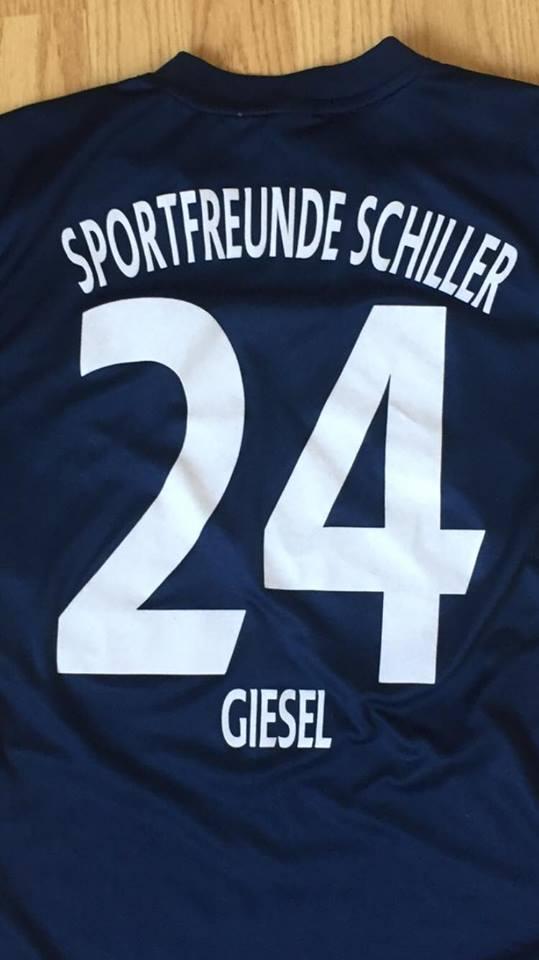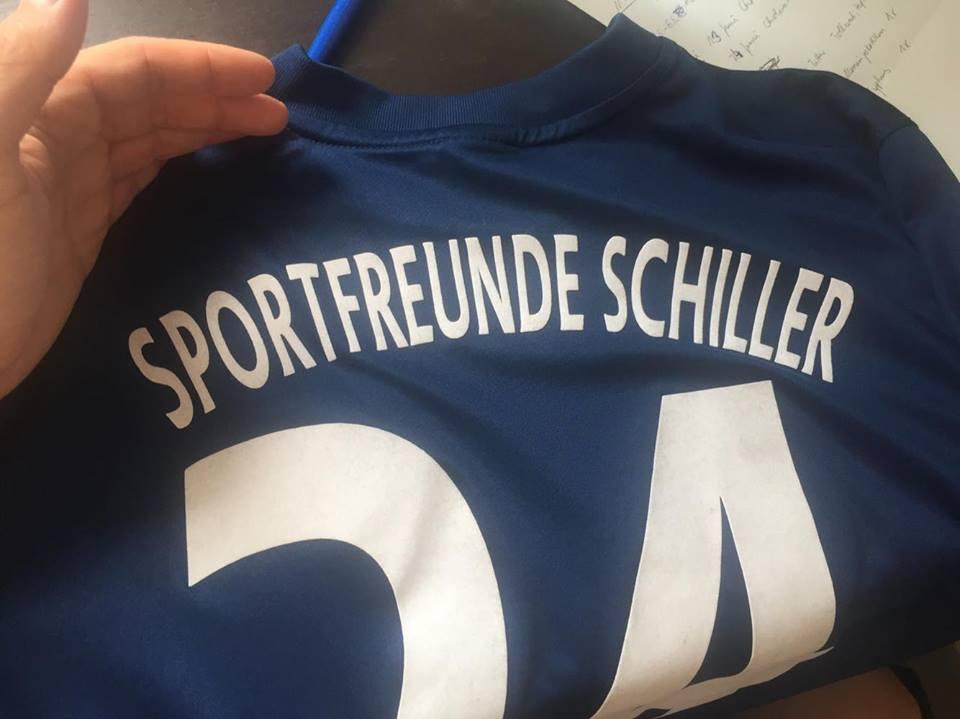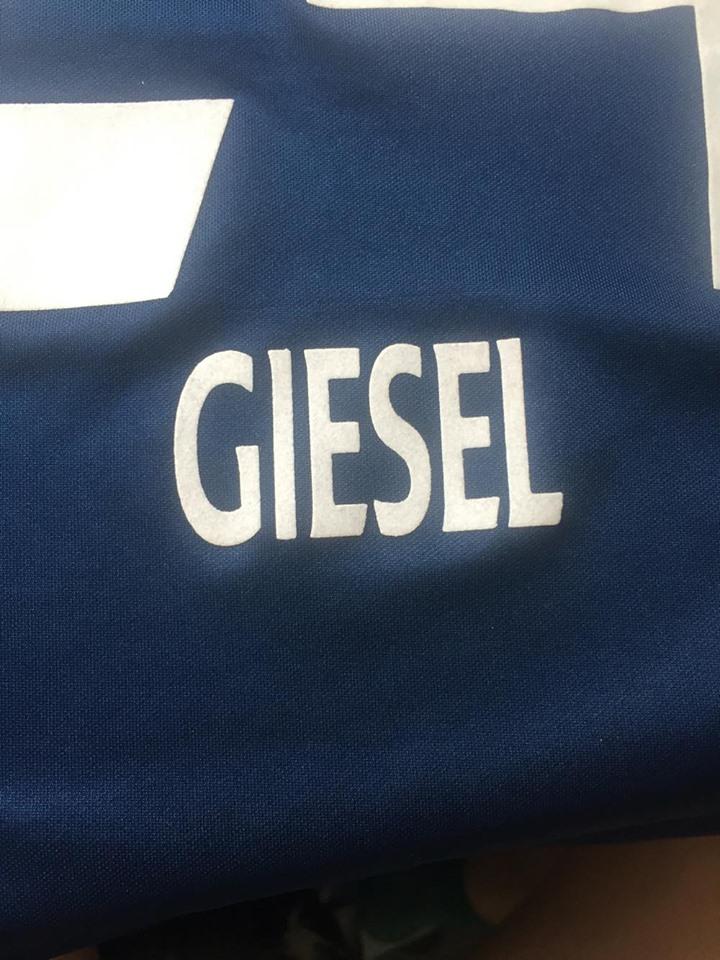
Schriftart auf Trikot
Hey, wollen Trikots nachdrucken lassen. Nun bekommen wir nicht genau raus, welche Schriftart diese haben. Wer kann uns helfen?
Bitte um dringende Antwort. Vllt weiss ja auch jemand was "Schriftart b" bei von der Internetseite "dein-fussballtrikot.de" ist . Den Anbieter scheint es leider nicht mehr zu geben.
"GIESEL" ist aus einer verzerrren "Premier League" gesetzt.
Und wenn es dir nicht zu viel Mühe macht, könntest du ein Bild der gesuchten "Schriftart b" posten. Meine Glaskugel ist grad beim Polieren …
Leider hab ich kein Bilder der "Schriftart b" nur eben auf dem Bestellschein steht , dass die Schriftart auf dem Trikot "Schriftart b" ist.
Die 24 sind sehr wahrscheinlich auch eine heftig gequetschte Premier League.